1. 배민체 시리즈 — 블로그 감성템 끝판왕
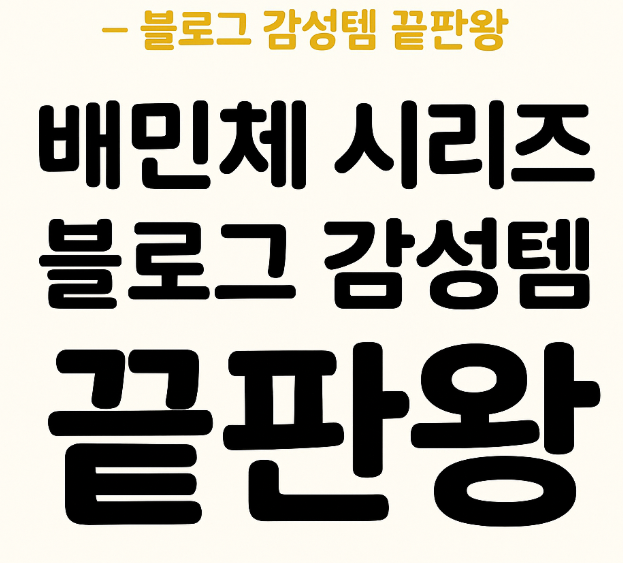
- 배민한나는열일체 / 배민다정체
- 귀여움 + 가독성 모두 갖춘 국민 감성 폰트
2. 빙그레체 — 부드러운 손글씨 느낌
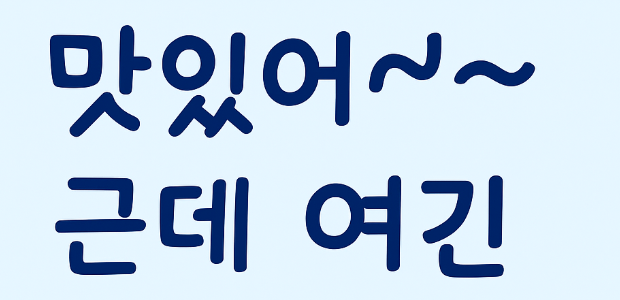
- 빙그레체 / 빙그레 따옴체
- 사랑스러운 인상 + 데일리 감성
3. 메로나체 — 여름 감성에 찰떡
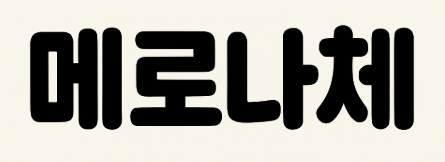
- 시원한 느낌 + 귀여운 터치
4. 서울한강체 — 정갈한 감성 + 깔끔함
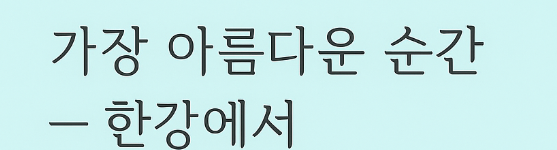
- 서울시에서 배포하는 공식 폰트
- 감성글/정보형 글에도 무난하게 활용 가능
5. 야놀자 야체 — 여행 블로그에 딱!
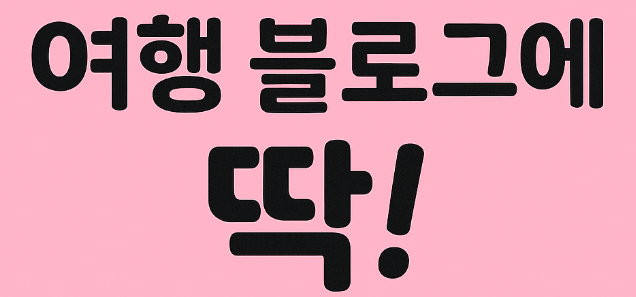
- 활기찬 인상 + 가독성도 우수
6. 카페24 써라운드체
- 소셜미디어 카드뉴스용으로 인기
- 미리캔버스에서 바로 사용 가능
7. 넥슨 Lv1 고딕체
- 디지털 감성 + 귀여운 마무리
- 게임/영상 썸네일에 잘 어울림